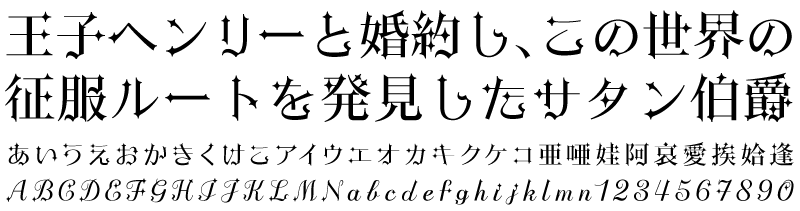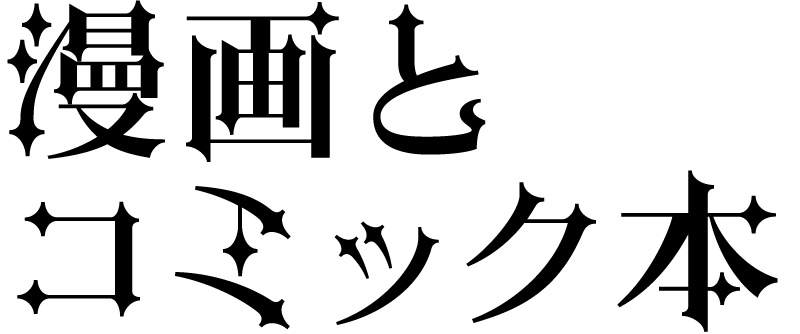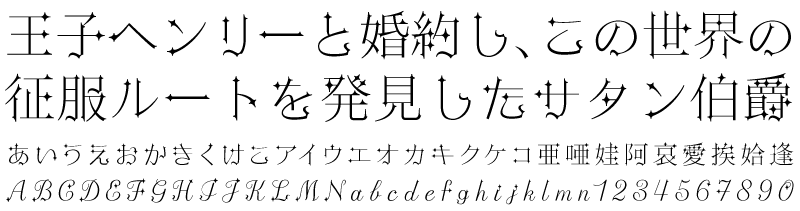
黒明朝の特徴
創作のコンセプトは、『明朝体の伝統的な気品を保ち、オリジナリティーを兼備すること』です。「うちこみ」は「矛」のごとく鋭いが、「はらい」はリボンのように優しくなびく。文字組みによって表情が変化します。文章の並びによる新奇性の出会いをお楽しみください。
黒明朝-L
黒明朝-M
黒明朝-B
黒明朝-EB
黒明朝-U